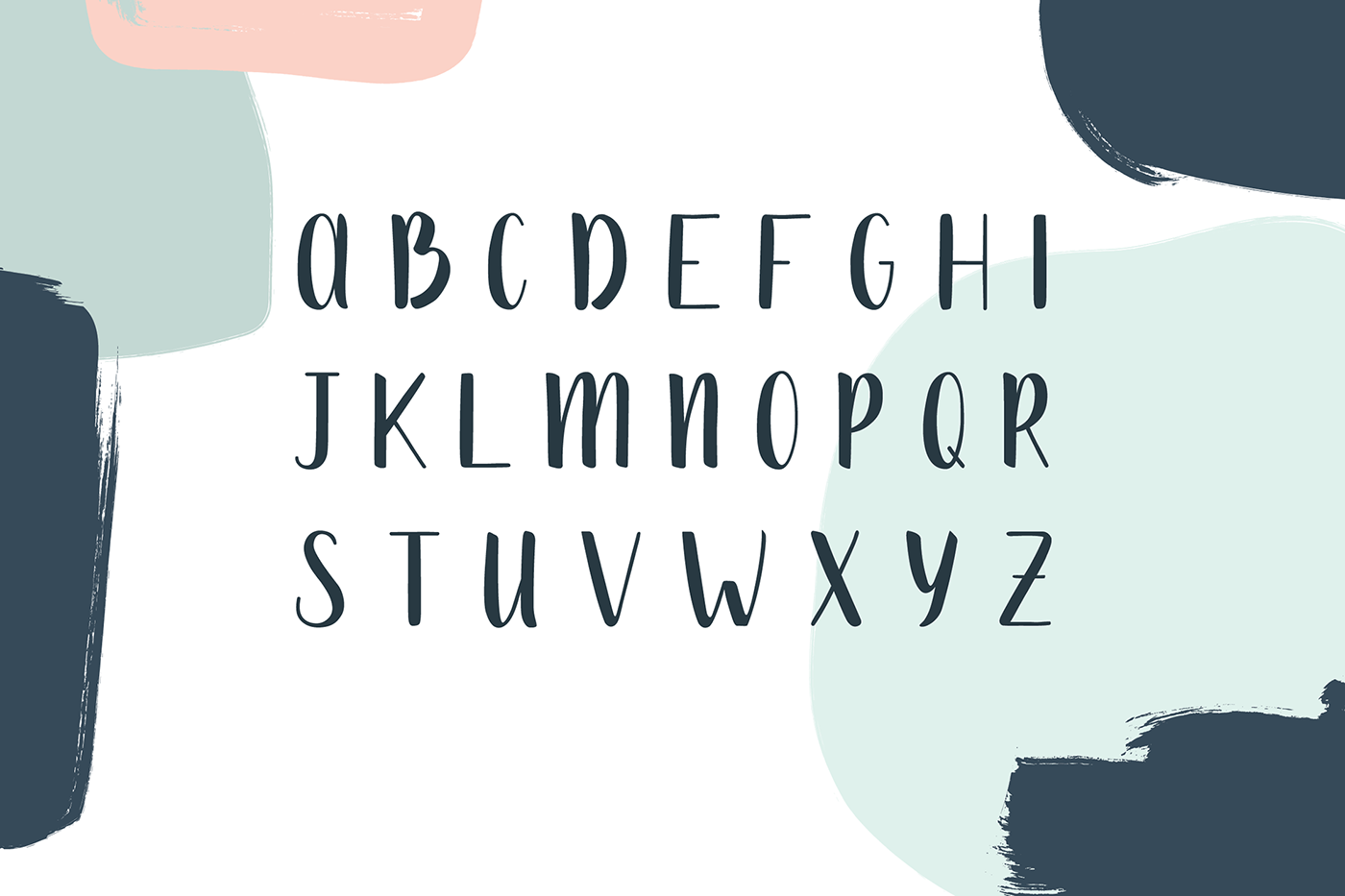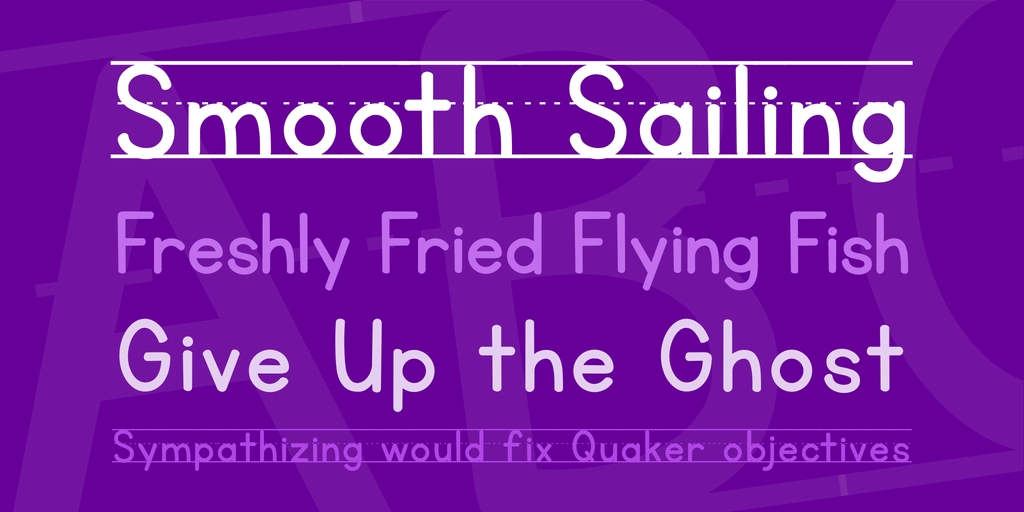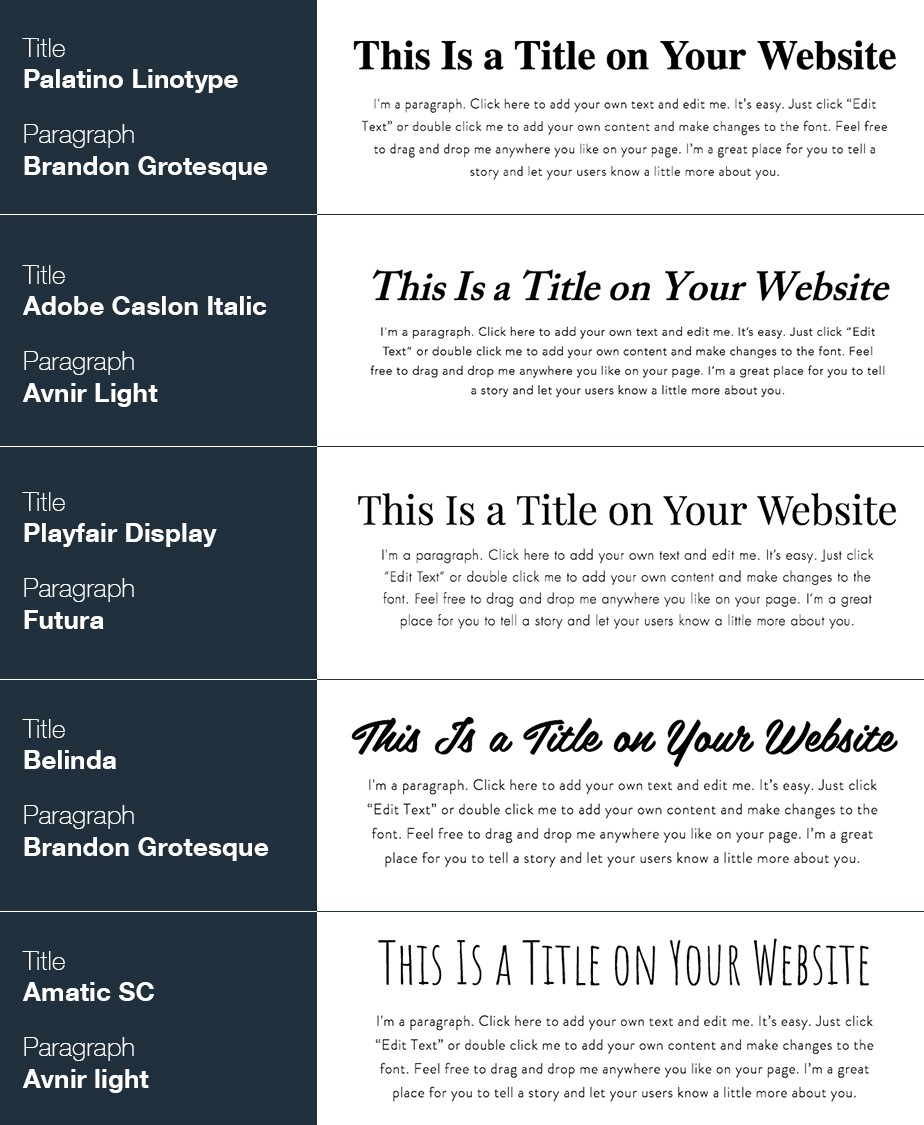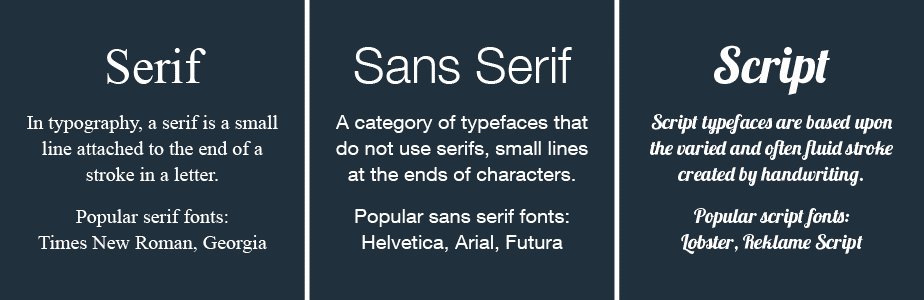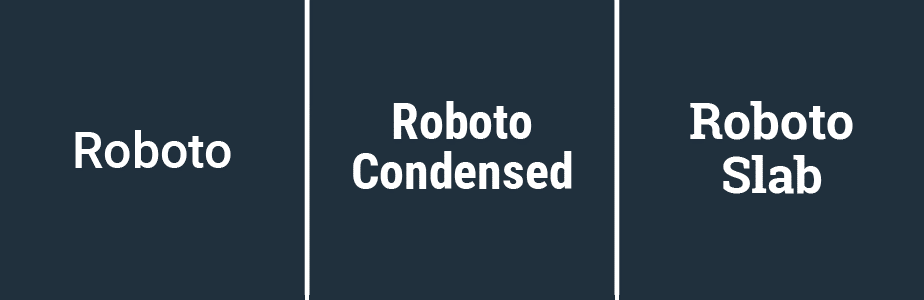
Làm thế nào để chọn phông chữ tốt nhất cho trang web của bạn
Khi nói đến thiết kế trang web tuyệt vời của bạn, có rất nhiều điều cần chú ý. Giữa việc viết nội dung của bạn, chọn hình nền hoàn hảo cho pixel và đảm bảo bạn đã kết nối các kênh truyền thông xã hội của mình nhưng có một số yếu tố bị bỏ lỡ và một trong những yếu tố đó là phông chữ.
Cách chọn font tốt nhất cho thiết kế website
Typography theo nghĩa đen có rất nhiều điều để nói, vì nó có thể gợi lên nhiều hơn chỉ là lời nói. Nếu bạn không phải là một nhà thiết kế giàu kinh nghiệm, vấn đề bạn có thể phải đối mặt là hiểu được kiểu chữ phù hợp với thương hiệu và giọng nói của bạn . Đừng lo lắng, vì chúng tôi sẽ đưa ra hướng dẫn hữu ích này để giúp bạn chọn phông chữ tốt nhất cho trang web của mình:
Cách chọn font tốt nhất cho thiết kế website
Đảm bảo phông chữ phù hợp với tông màu của thương hiệu
Khi nói đến phông chữ của bạn, web an toàn hay không, bạn muốn đảm bảo phông chữ phù hợp với danh tính của thương hiệu. Xu hướng chính xác là: xu hướng. Chỉ vì Tuần lễ thời trang nhìn thấy một con kỳ lân đi xuống đường băng không có nghĩa là bạn cũng sẽ mặc đồ giống màu của chú kỳ lân.
Cách chọn font tốt nhất cho thiết kế website
Cũng vậy với sự hiện diện trực tuyến của bạn. Bạn không cần phải tuân theo các xu hướng nếu chúng không thể đáp ứng những gì bạn đang cố gắng thực hiện. Nếu nó không khớp với trang của bạn.
Vì vậy, năm 2018 có thể được mô tả là năm thiết kế “táo bạo”, nhưng mối quan tâm chính của bạn là nên làm sao có thể thiết kế trang web với phong cách của riêng bạn. Luôn nhớ những gì Coco Chanel thường nói: "Thời trang mất dần, chỉ có phong cách là còn mãi."
Xếp hạng phông chữ của bạn theo mức độ quan trọng
Hãy nhớ rằng bạn không nên sử dụng nhiều hơn ba phông chữ trên trang web của mình. Hơn nữa, mỗi phông chữ này phải có các mức độ quan trọng khác nhau. Khi chọn bảng màu, quá trình này thường bao gồm việc tìm màu chính, màu phụ và màu nhấn. Về cơ bản, bạn có thể sử dụng cùng một mẫu với kiểu chữ của mình:
Phông chữ chính của bạn là phông chữ dễ thấy nhất và nên được sử dụng trên tiêu đề của trang web của bạn. Thật khôn ngoan khi sử dụng phông chữ phù hợp phong cách logo của bạn nếu có văn bản trong đó. Nói chung, đây là loại phông chữ nên có thể nhận dạng nhất với thương hiệu của bạn, ngay cả khi nó không được sử dụng nhiều nhất trên trang web của bạn.
Cách chọn font tốt nhất cho thiết kế website
Phông chữ phụ của bạn phần lớn sẽ bao gồm nội dung văn bản ‘thịt’ của bạn. Điều này bao gồm các đoạn văn, mô tả, bài viết trên blog, v.v. Trong khi phông chữ chính có thể hấp dẫn và nguyên gốc, mục tiêu chính của bạn cho phông chữ phụ là tính dễ đọc. Đừng mong đợi các khách hàng tiềm năng tìm hiểu sản phẩm / dịch vụ của bạn.
Cuối cùng, Điểm nhấn phông chữ là chữ mà bạn sẽ sử dụng cho một mục đích rất cụ thể. Khi nói đến các trang web, điều này thường dành riêng cho các lời gọi hành động. Để thu hút đôi mắt (và nhấp chuột) của khách truy cập, bạn sẽ muốn chọn một kiểu chữ nổi bật so với phần còn lại của các trang.
Nếu bạn cần một số trợ giúp trộn và kết hợp phông chữ cho trang web ALI của bạn, dưới đây là các phông chữ được nhà thiết kế yêu thích.
Cách chọn font tốt nhất cho thiết kế website
Bạn có thể biết sự khác biệt giữa các phông chữ Gothic, Roman và Grotesque. Nhưng có rất nhiều điều để nói về các loại phông chữ. Trang web này, ví dụ, sẽ dạy cho bạn rất nhiều về lý thuyết về kiểu chữ. Tuy nhiên, khi bạn bắt đầu, bạn nên tập trung vào phân loại quan trọng nhất: serif, sans serif và font chữ. Dưới đây là tóm tắt nhanh về từng loại và thời điểm sử dụng chúng:
Phông chữ Serif đã được sử dụng rộng rãi với các bản in (sách, báo, vv). Chữ ‘serif’ là một dòng nhỏ gắn vào phần cuối của dấu trong một ký tự hoặc ký hiệu. Đối với phông chữ, dòng ‘serif’ có thể được tô điểm theo nhiều cách khác nhau để cho nó có giao diện độc đáo riêng. Phông chữ Serif được coi là cổ điển và thanh lịch hơn, và sẽ nói chuyện với khán giả lớn tuổi hơn.
Phông chữ Sans serif chỉ là phông chữ không có dòng serif được đính kèm. Đây là những phù hợp hơn cho màn hình máy tính và điện thoại thông minh. Đây là lý do tại sao bạn chủ yếu sẽ tìm thấy việc sử dụng phông chữ sans serif trên hầu hết các trang web. Không ngạc nhiên, khi nó là lựa chọn ưu tiên của giới trẻ.
Phông chữ tập lệnh được mô hình hóa theo phong cách chữ viết tay của thế kỷ 17. Giống như hầu hết các loại phông chữ, tập lệnh có tập con riêng của nó, được chia thành các biến thể chính thức và giản dị. Nếu bạn thực sự muốn thu hút sự chú ý bằng văn bản của mình, thì phông chữ này sẽ giúp bạn làm điều đó
Cách chọn font tốt nhất cho thiết kế website
Nắm vững nghệ thuật pha trộn phông chữ
Hàng trăm phông chữ tuyệt đẹp đang chờ bạn trong ALI Editor, miễn phí. Và nếu bạn có một ý tưởng khác (mà bạn tự tạo ra hoặc mua từ một nhà thiết kế) thì đó không phải là vấn đề! Bạn có thể dễ dàng tải phông chữ của riêng mình lên Trình chỉnh sửa chỉ trong vài cú nhấp chuột. Bây giờ bạn đã biết nơi để tìm phông chữ và nơi đặt phông chữ, hãy nói một chút về cách trộn chúng.
Điều đầu tiên bạn nên làm là nhận thêm một số trợ giúp từ FontPair. Giống như tên cho thấy, nó sẽ hiển thị cho bạn các kết hợp phông chữ để bạn có thể đảm bảo rằng bạn đã chọn cặp tốt nhất cho thương hiệu và trang web của mình.
Một cách chắc chắn để duy trì tính nhất quán, trong khi cung cấp các biến thể, là chọn các phông chữ khác nhau trong cùng một gia đình cho chính và phụ
Cách chọn font tốt nhất cho thiết kế website
Biết trọng lượng (và kích thước) của các từ của bạn
Khi nói đến phông chữ (ít nhất), kích thước không quan trọng. Khi bạn đã chọn lược đồ loại, bạn sẽ cần quyết định kích thước cho các tên sách lớn, phụ đề và văn bản đoạn. Ví dụ, đây là những phạm vi mà chúng tôi đề xuất cho phông chữ của Trình chỉnh sửa ALI - nhưng chúng có thể là hướng dẫn tốt cho bất kỳ trang web nào:
• Tiêu đề: 30-70
• Phụ đề: 22-30
• Đoạn: 16-20
Trên đầu trang của kích thước, nhiều yếu tố khác sẽ ảnh hưởng đến "trọng lượng" trực quan của một phông chữ, chẳng hạn như nhấn mạnh với chữ đậm, in nghiêng hoặc gạch dưới. Tuy nhiên, việc sử dụng quá nhiều các kiểu này có thể làm mất phong cách của mình.
Viết với các xu hướng trong đầu
Thiết kế khôn ngoan, năm 2019 sẽ là một năm rất sáng tạo, do đó, nhiều nhà thiết kế mong đợi để xem bố cục táo bạo và bảng màu trên toàn bộ web. Đây cũng là xu hướng bạn có thể áp dụng cho phông chữ của mình, chọn kiểu chữ kỳ lạ. Ngoài việc “táo bạo”, thứ bạn sẽ bắt đầu thấy nhiều hơn là ghép đôi serif và sans serif.
Trước đây, một thiết kế “no-no” hiện đã được chào đón vì vậy nếu bạn cảm thấy phù hợp với thương hiệu của mình, hãy thực hiện nó. Các tiêu đề và tiêu đề phụ của trang web của bạn sẽ là nơi tốt nhất để áp dụng phông chữ funky. Một thực tế thú vị rằng theo một số nghiên cứu tiếp thị, việc thêm một phông chữ phức tạp hơn có thể làm chậm trình đọc của bạn. Điều này mang lại cho họ nhiều thời gian hơn để hiểu được thông điệp của bạn.